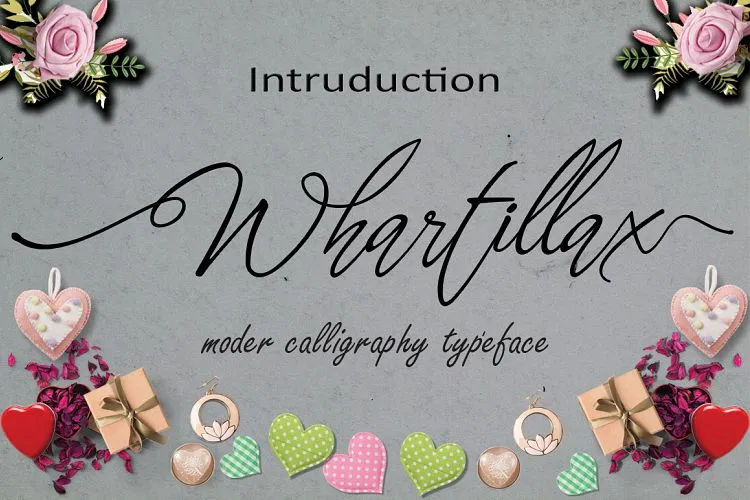
Whartillax Calligraphy Font – Download Grátis
A Whartillax Calligraphy Font é uma delíciada escolha para quem deseja adicionar um toque elegante e sofisticado a qualquer projeto tipográfico. Esta fonte script é perfeita para gráficos de newsletter, editoriais de moda ou até mesmo em designs de cartões de aniversário. Suas letras fluidas e delicadas são projetadas para transmitir calma e autenticidade, criando um design que traz ar fresco e charme a qualquer projeto. A Whartillax Calligraphy é uma fonte que realmente faz as pessoas olharem duas vezes, permitindo-lhes explorar cada detalhe em seus designs, desde as curvas elegantes até o acabamento delicado. Com sua versão do Designer 178-MC, a Whartillax Calligraphy é uma excelente adição para qualquer designer que busca dar vida e um toque de personalidade ao seu trabalho.